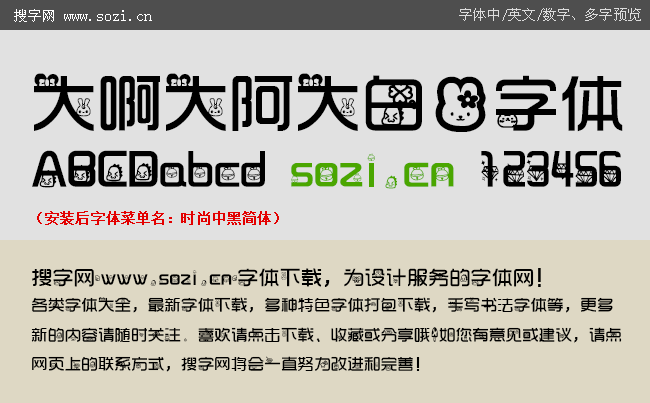
大啊大阿大白兔字體
搜字網(wǎng)給大家提供一款很有趣的手機(jī)中文字體下載。修改者給他起了個(gè)大啊大阿大白兔字體這么萌的名字,這款手機(jī)字體是在時(shí)尚中黑字體上進(jìn)行修改,筆畫間插入了有趣的卡通動(dòng)物圖案。真是趣味性實(shí)足的一款手機(jī)字體,該中文字體個(gè)性實(shí)足,趣味性強(qiáng),又保持了文字的識(shí)別度,特別適合喜歡手機(jī)字體個(gè)性一些的朋友在手機(jī)上安裝使用。